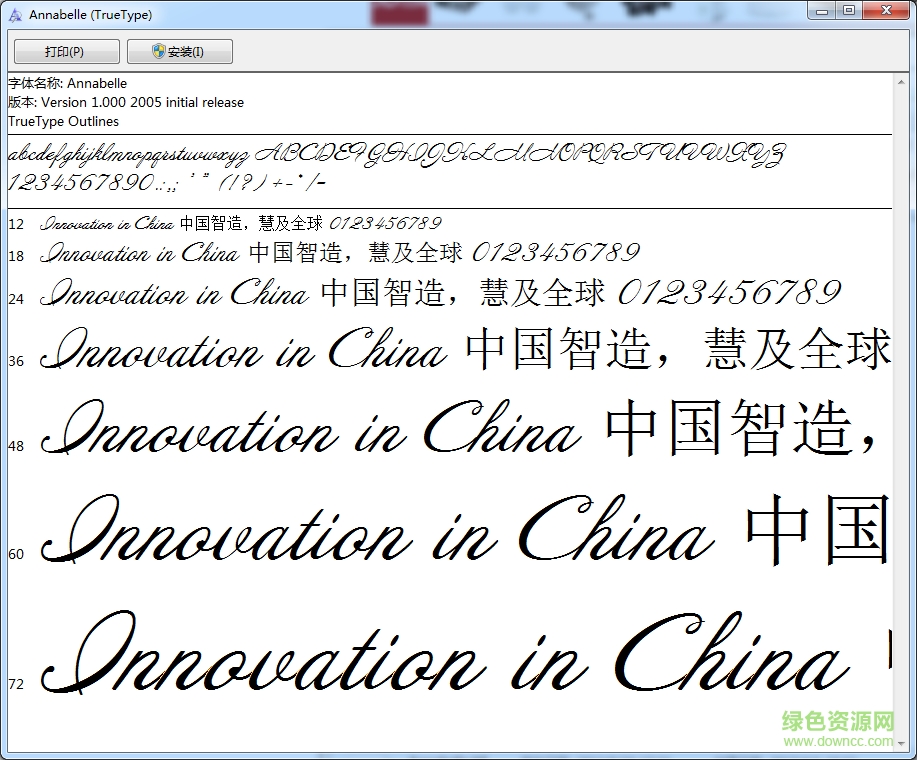
Annabelle字體
Annabelle是一款極具美感的花體英文字體,字體向右傾斜,支持多種文字輸入,字體線條好簡(jiǎn)潔給人以美的享受,下載安裝即可使用??靵砭G色資源網(wǎng)下載體驗(yàn)阿布!
Annabelle字體介紹
Annabelle是一看非常漂亮的藝術(shù)字體,這款字體字體生動(dòng)活潑,還帶有漂亮的天使翅膀,整體效果非常出色。